Tổng quan về Summitsoft FontPack Pro Master Collection: 7.400 font OpenType cao cấp
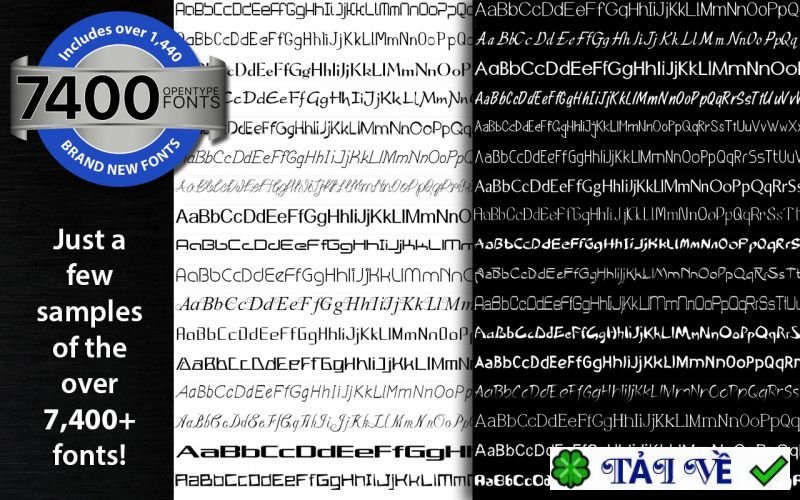
Summitsoft FontPack Pro Master Collection là một bộ sưu tập phông chữ toàn diện do Summitsoft Corporation cung cấp. Bộ sưu tập này bao gồm hàng ngàn font chữ đa dạng, phục vụ mọi nhu cầu thiết kế, từ đồ họa, web, bài thuyết trình cho đến xây dựng thương hiệu. Với nhiều phong cách khác nhau, từ cổ điển, tinh tế đến hiện đại, độc đáo, bộ sưu tập này đáp ứng mọi gu thẩm mỹ và yêu cầu sáng tạo.
Toàn bộ các Font chữ Sáng tạo đều sử dụng định dạng OpenType, một tiêu chuẩn công nghiệp được Microsoft và Adobe tin dùng, đảm bảo font chữ luôn sắc nét và rõ ràng ở mọi kích thước. Sở hữu hơn 7.400 font chữ cho phép sử dụng thương mại, FontPack Pro Master Collection là sự bổ sung giá trị cho bộ công cụ sáng tạo của bạn, đi kèm giấy phép sử dụng thương mại cho mọi dự án cá nhân.
Các tính năng nổi bật của Summitsoft FontPack Pro Master Collection
Chất lượng cao & Đa dạng
- Mọi Font chữ Sáng tạo đều là OpenType, một định dạng chuẩn công nghiệp của Microsoft® và Adobe®, giúp đảm bảo font chữ hiển thị sắc nét, rõ ràng ở mọi kích thước.
Bộ ký tự đầy đủ
- Mỗi phông chữ sáng tạo đều bao gồm bộ ký tự đầy đủ, cùng với các ký hiệu quốc tế và ký tự đặc biệt, đáp ứng mọi yêu cầu ngôn ngữ và biểu tượng.
Lợi ích của định dạng OpenType